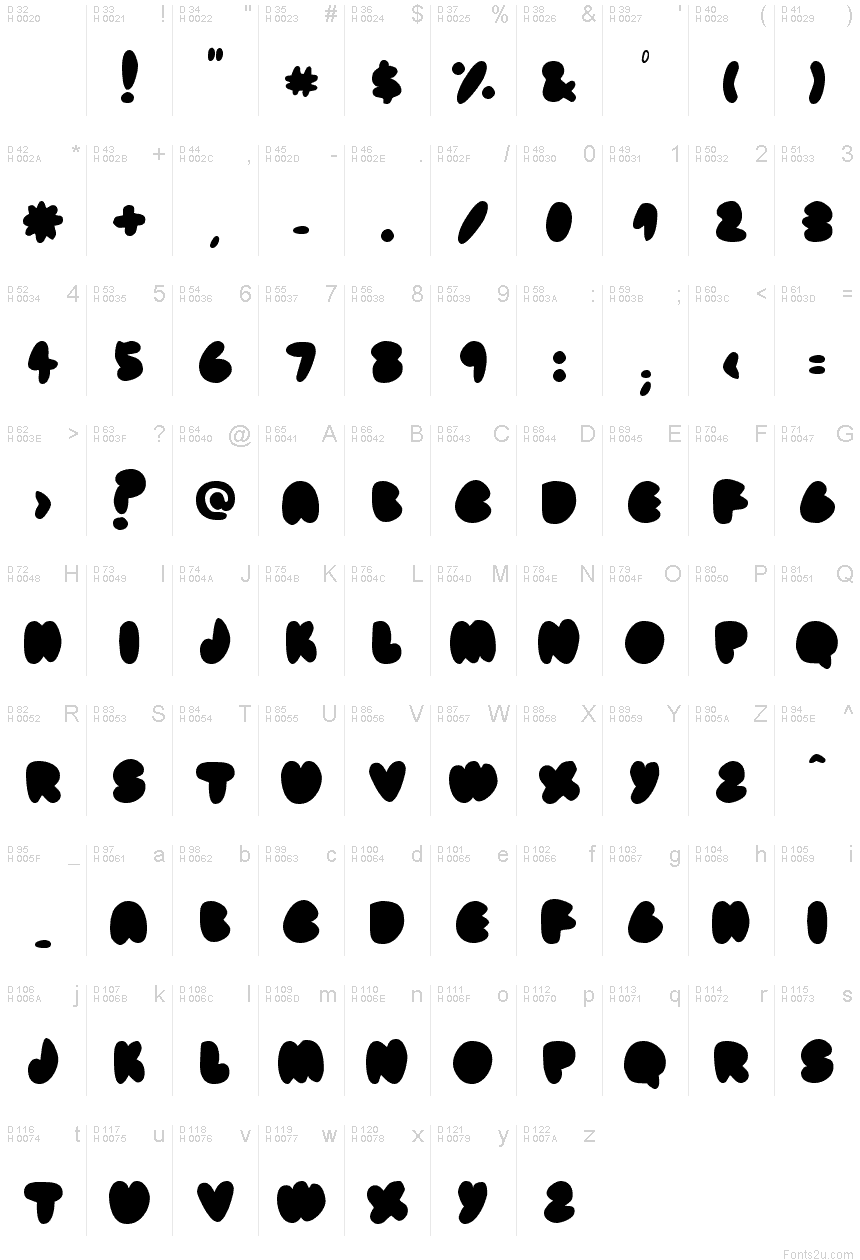
Fat Ass Filled to darmowy, rysunkowy font typu display z miękkimi, napęczniałymi literami, które wyglądają jak uformowane, a nie narysowane. Wielkie litery opierają się na dużych, zaokrąglonych sylwetkach, zwężonych łączeniach i ciężkiej, niemal kluchowatej wadze, nadając czcionce figlarnego klimatu lat 70., bez zbędnego przekombinowania.
Pasuje do plakatów, opakowań przekąsek, grafik na imprezy dla dzieci, zabawnych szkiców logo i krótkich nagłówków w mediach społecznościowych, gdzie ten darmowy font o tak dużej objętości może szybko przykuć uwagę. Wykorzystaj go do kart tytułowych, nagłówków czy inicjałów w stylu monogramów, gdy chcesz, aby litery czytało się najpierw jako wyraziste kształty, a dopiero potem jako słowa.